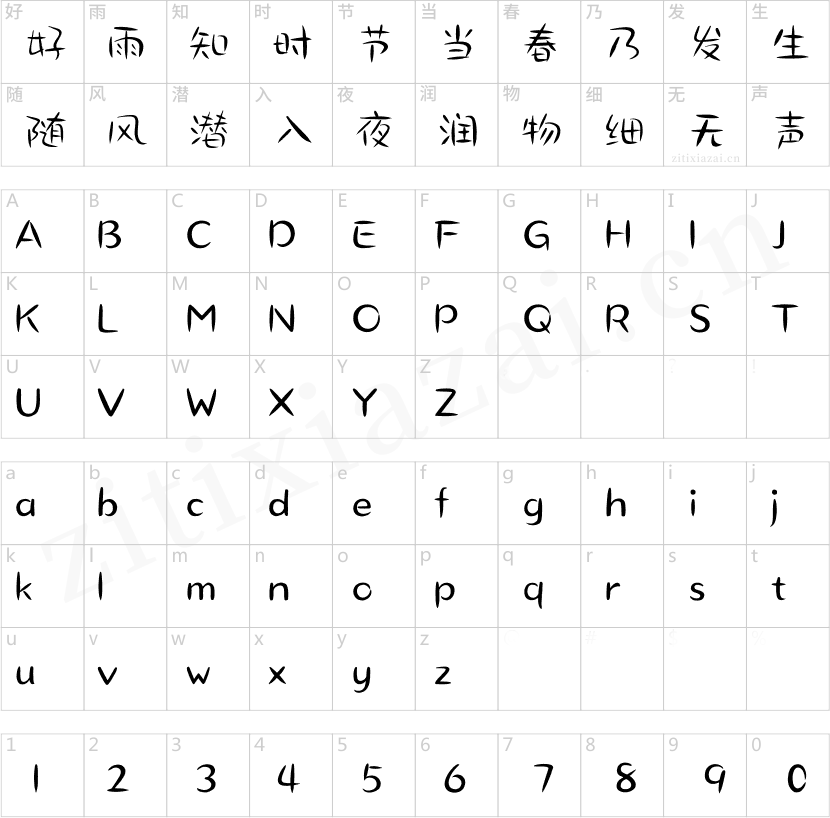
汉仪风波柳叶体
汉仪风波柳叶体,这款字体结构工整、笔画清晰,兼顾美观与易读性,适用于标题、正文、海报、包装、LOGO 等多种场景。字形优雅稳定,风格百搭耐看,适配日常排版与创意设计,让文字呈现更舒适、更具质感。汉仪风波柳叶体一笔一画,皆是细节,以均衡的比例、流畅的线条打造舒适视觉体验,字形端正大气,风格简约现代。无论是商业设计、品牌宣传还是日常排版,都能轻松驾驭,让文字更有格调与力量。汉仪风波柳叶体字体下载。